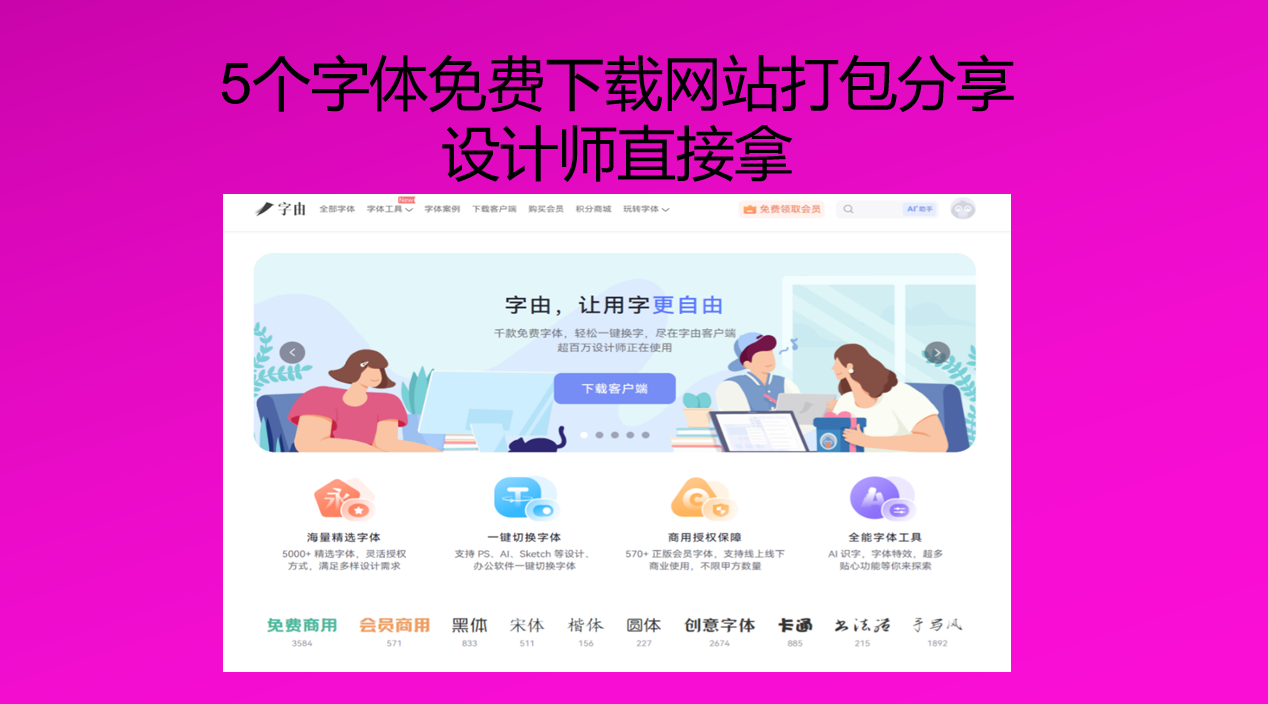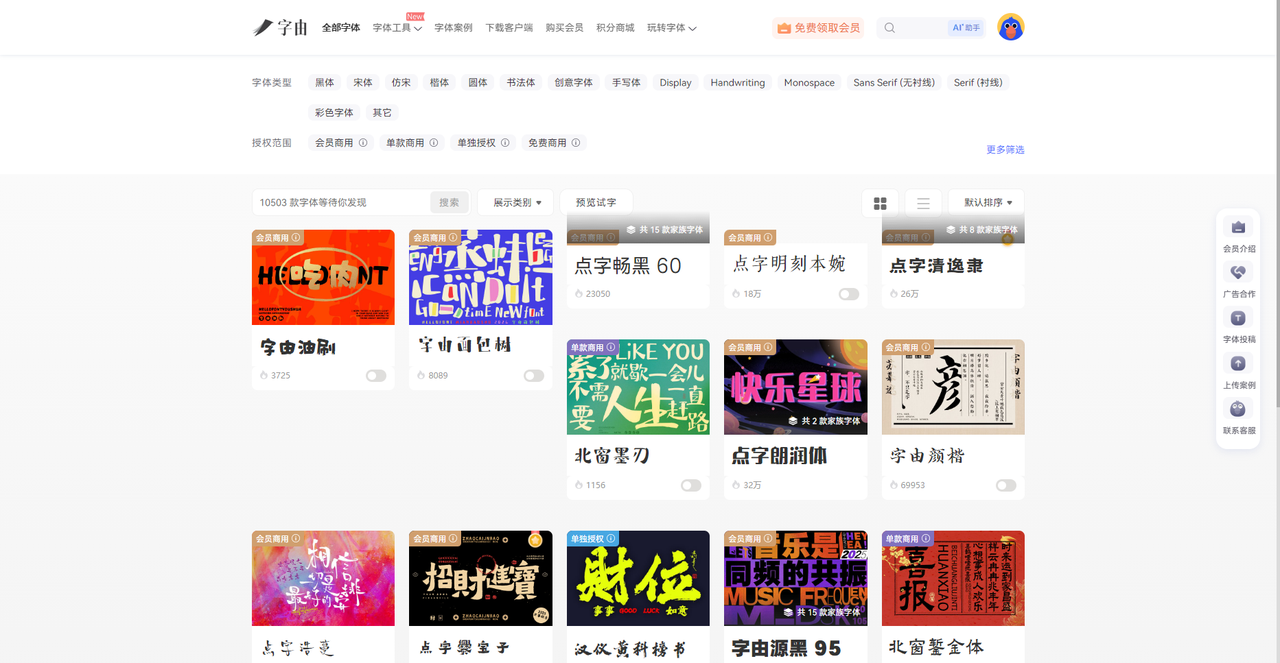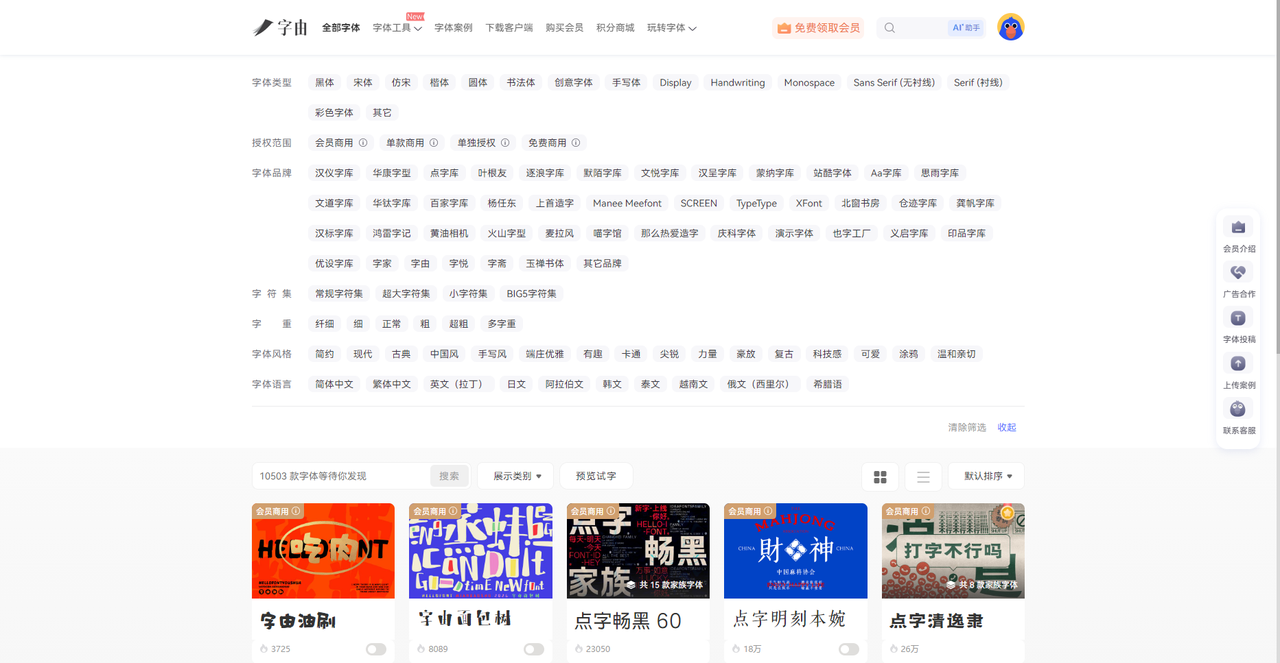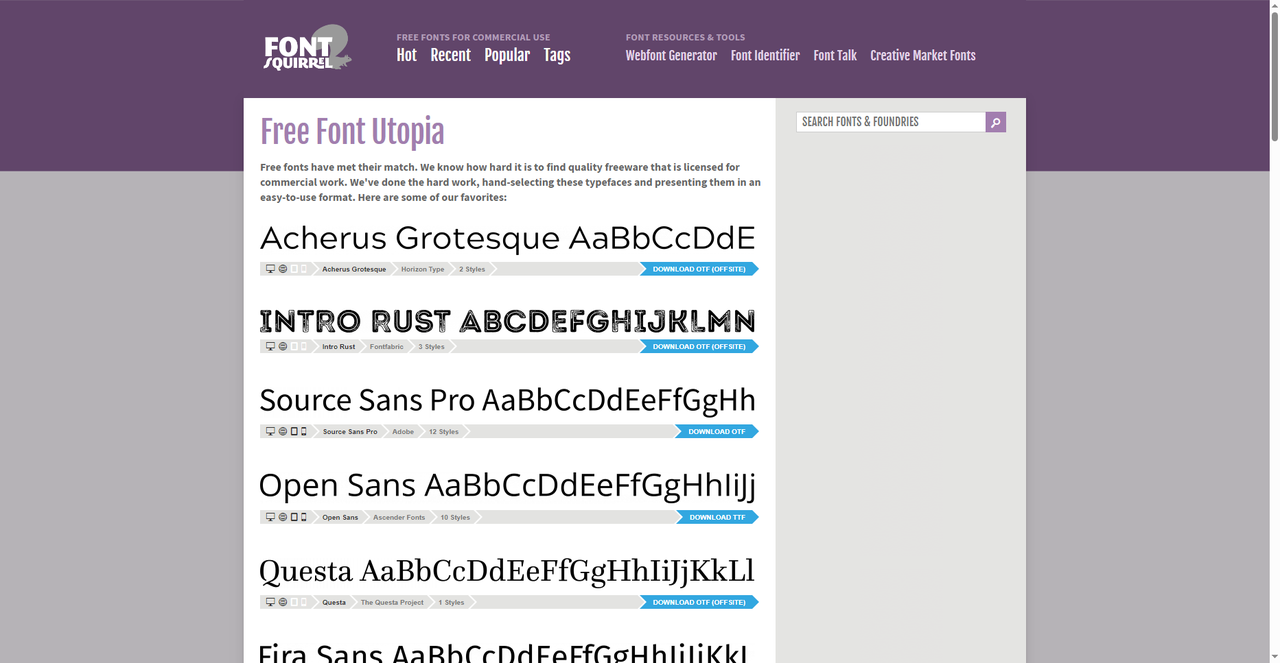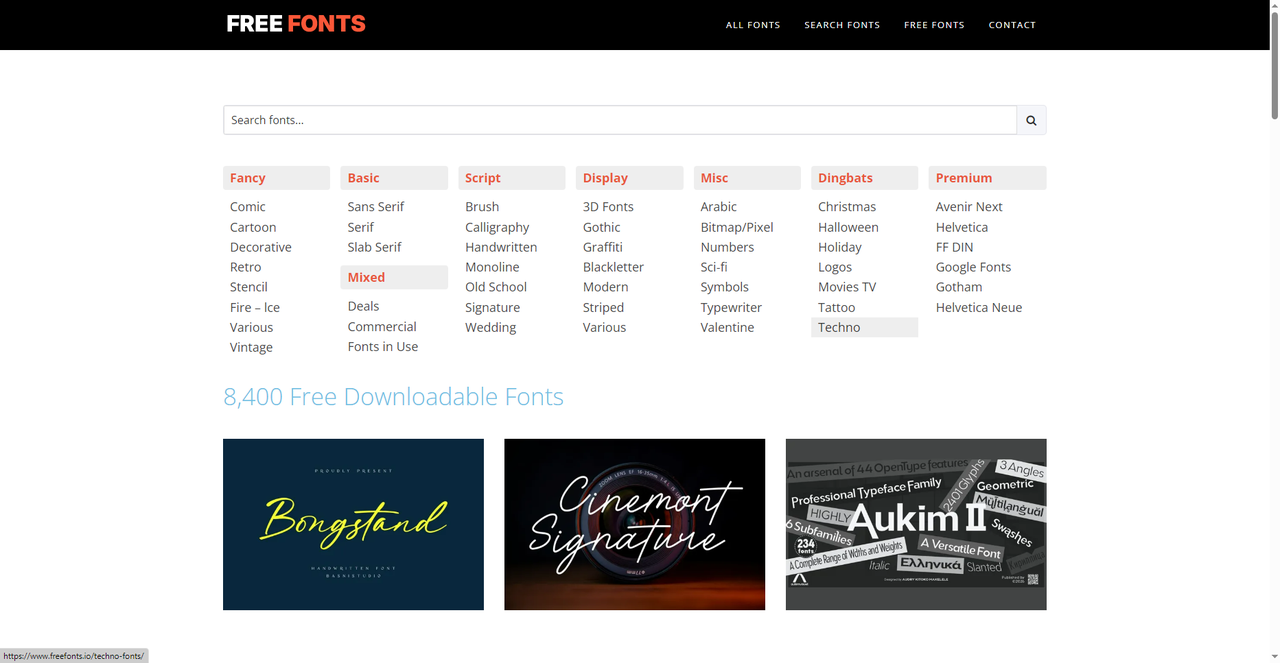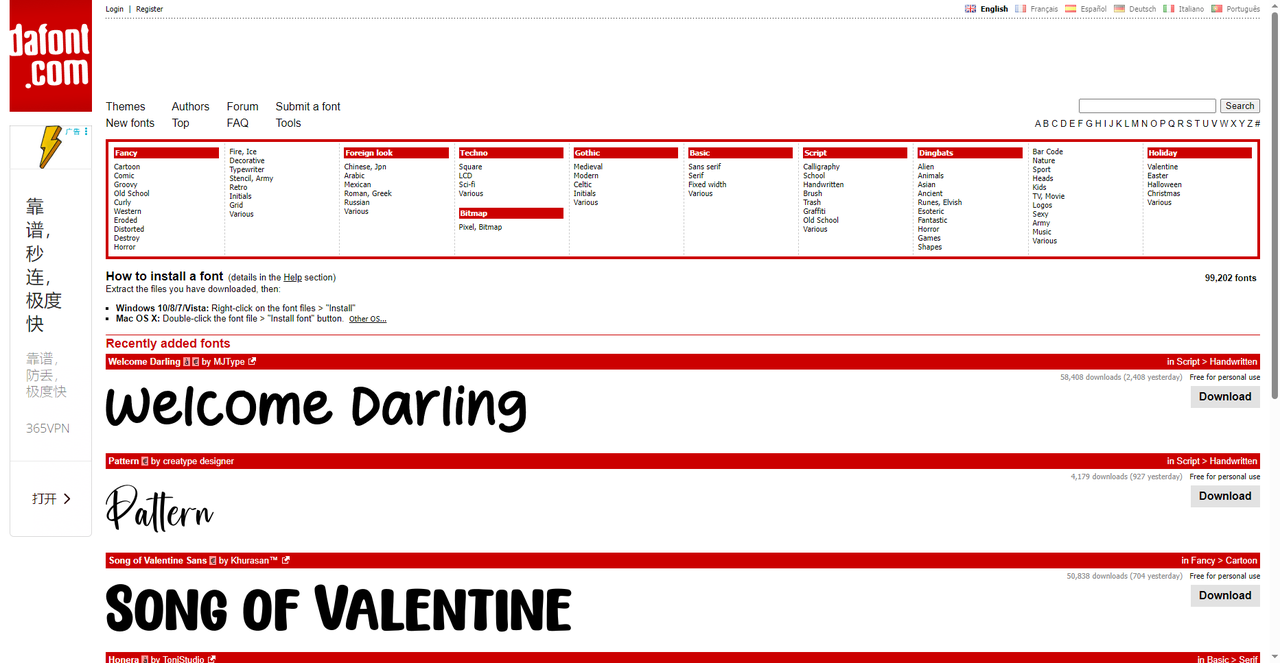
4个字体免费下载网站打包分享,设计师直接拿
之前有很多人问过我,说我在用的这些字体都是从哪里下载的,我每次的回答无一例外都是说是从我最常用的几个字体免费下载网站下载的,直接在网站里挑选好字体,看好下载说明和授权类型以后就可以拿来使用了。只需要在用的时候去翻一翻即可,那么今天我就会把我私藏的4 个字体免费下载网站一次性分享出来,从国产神器字由到国外老牌平台,每个都亲测好用。需要的直接拿走,省下到处找字体的时间。
第一个要推荐的字体免费下载网站是字由。很多人知道字由是字体管理神器,但其实它本身就是一座巨大的免费字体库。最重要的是它不只是给你提供下载字体的平台,还有很多实用的功能辅助你进行设计工作。接下来我会详细介绍它的用法:
1. 丰富的字体库
字由目前收录了超过10500款字体,其中3584款是免费可商用的。这个体量意味着什么?就是你日常设计需要用的黑体、宋体、书法体、手写体、艺术体,基本都能在这里找到。而且这些字体都来自正规厂商的公开授权,比如优设好身体、字由文艺黑、阿里妈妈东方大楷、阿里妈妈普惠体、抖音美好体等热门款,全部免费商用,用着放心。
1. 字体筛选功能
字由的筛选功能非常强大。点开“全部字体”,就可以看到有详细的筛选栏:
• 按类型:黑体、宋体、书法体、手写体、Sans Serif、Serif等
• 按授权:直接点“免费商用”,3584款随便挑
• 按热度:每款字体右下角有使用次数,优先选热度高的,比如“优设标题黑”使用量超1000万次
• 按品牌:汉仪字库、蒙纳字库、Aa字库等官方合作品牌专区,品质有保障
1. 热门字体推荐
字由里热度高又实用的免费字体不少,我会挑几款常用的来给大家进行分享:
• 优设标题黑:方正有力,适合海报标题、电商主视觉
• 字由文艺黑:既有黑体稳重又带手写感,适合品牌标题
• 思源黑体 Medium:经典开源字体,适合正文排版、UI界面
• 字由芳华体:温柔手写风,适合文艺类、生活记录
• 江西拙楷:朴拙手写感,适合国风、文创设计
1. 个人云字库
1. 品牌保障,无须担心
字由和汉仪、蒙纳、Aa字库、华康等知名字体厂商深度合作,开设了品牌字库专区。这些厂商的字体品质高、授权正规,如果你对字体有更高要求,可以直接逛品牌专区,每一款都拿得出手。
2、Font Squirrel
Font Squirrel 也是一个字体免费下载网站,它的口号是“Free Font Utopia”(免费字体乌托邦)。网站首页就写着:“我们深知找到授权用于商业工作的免费字体有多难,因此手动挑选了这些字体。”每一款都是人工审核,确保真正免费可商用。这也是我喜欢用这个网站的原因,因为它甚至避免了筛选,可以直接使用。这里我也会做一些推荐:
• Acherus Grotesque:现代无衬线体,3种字重
• Intro Rust:粗犷有力,适合标题
• Source Sans Pro:Adobe出品,10种字重,经典开源字体
• Questa:优雅衬线体,适合正文
Font Squirrel 的字体质量普遍很高,而且下载前有详细的预览和字符集展示。它还提供网页字体生成器,方便网页设计师使用。
3、FREEFONTS
这款字体免费下载网站的字体量也十分巨大,目前收录了8400款免费字体。左侧分类栏极其详细:
• Fancy:Comic、Cartoon、Decorative、Retro等
• Basic:Sans Serif、Serif、Slab Serif等
• Script:Brush、Calligraphy、Handwritten、Monoline等
• Display:3D Fonts、Gothic、Graffiti、Blackletter等
这种分类的好处是,你可以根据项目需求快速定位——比如要做万圣节海报,直接点Halloween;要做纹身设计,点Tattoo。不用在一堆字体里盲目翻。每款字体都有预览图,下载前还能输入自己的文字试效果。最主要的是需要留意授权说明!
4、DaFont
DaFont 是一个运营了二十多年的老牌字体免费下载网站,很多设计师第一次找字体都是从它开始的。它的分类非常传统但实用,首页会展示最新上传和热门的字体,比如“Welcome Darling”、“Pattern”、“Song of Valentine Sans”等。每款字体都有详细的安装说明和授权标注。DaFont 的字体多为个人免费使用,商用需仔细查看授权或购买。如果你想找一些有特色的小众字体,来这里逛逛总能有意外收获。